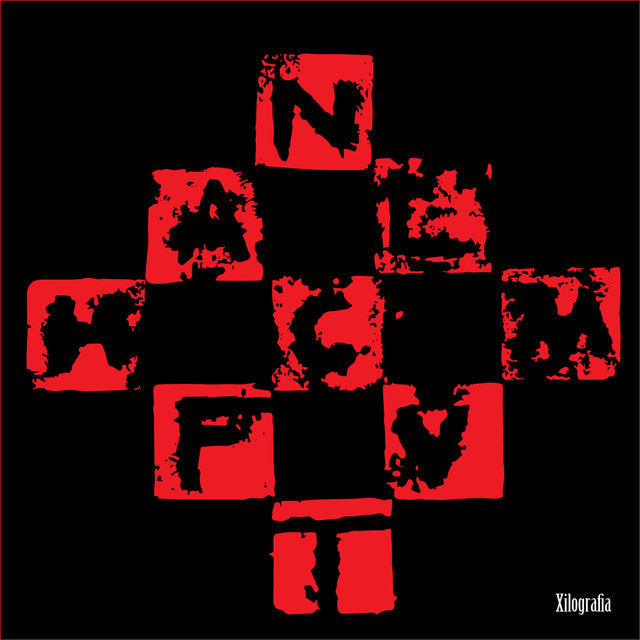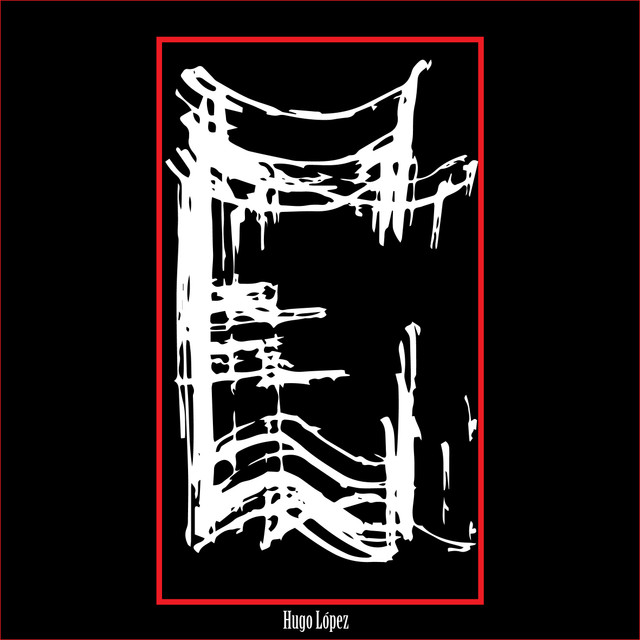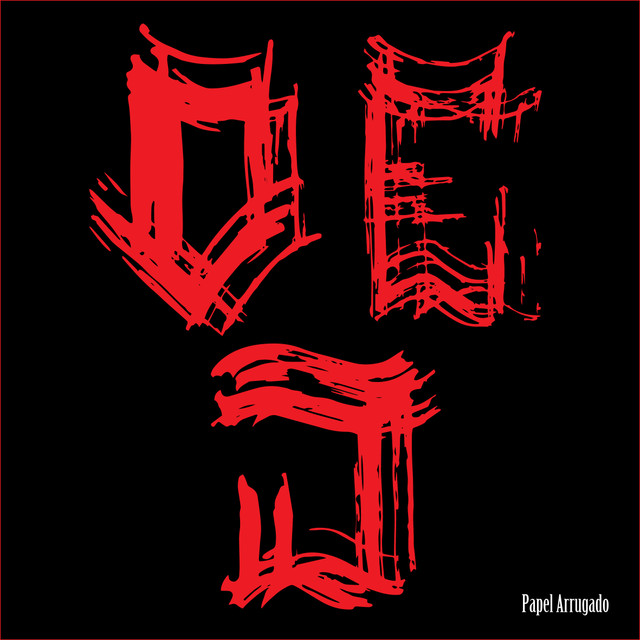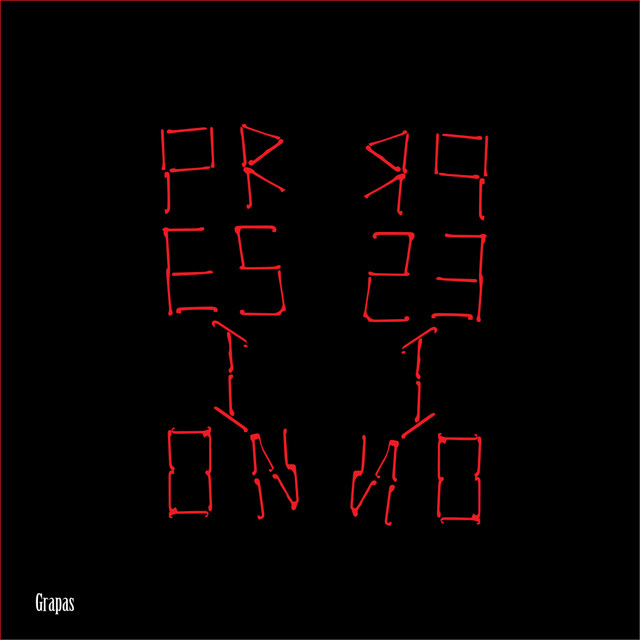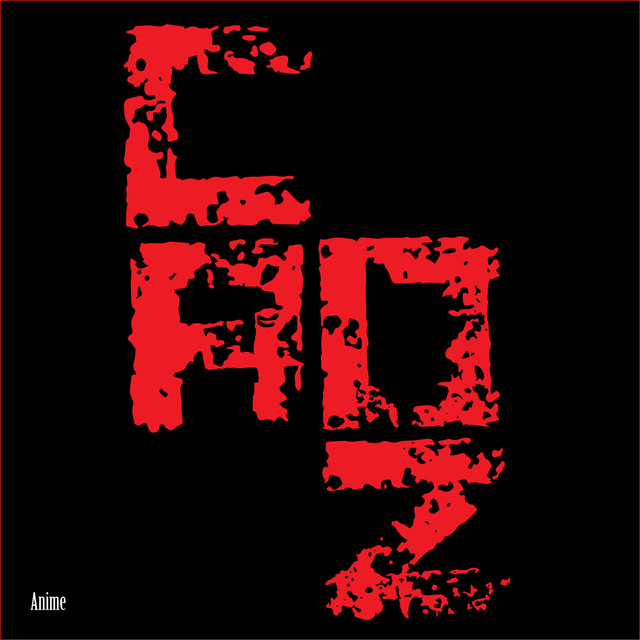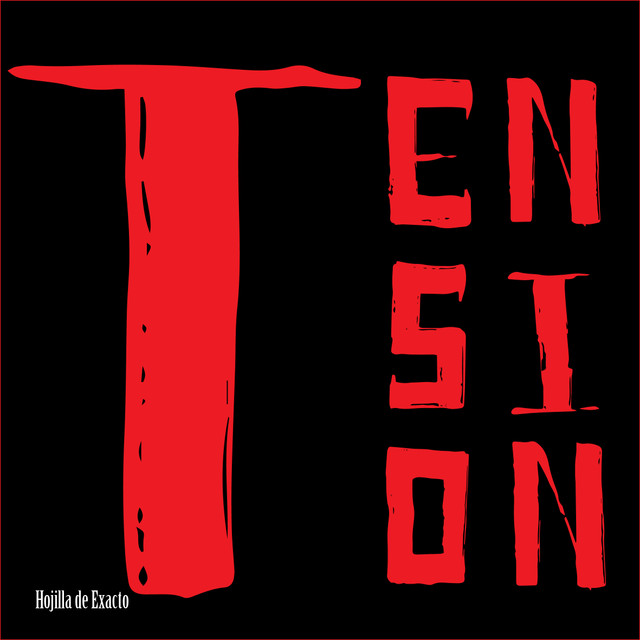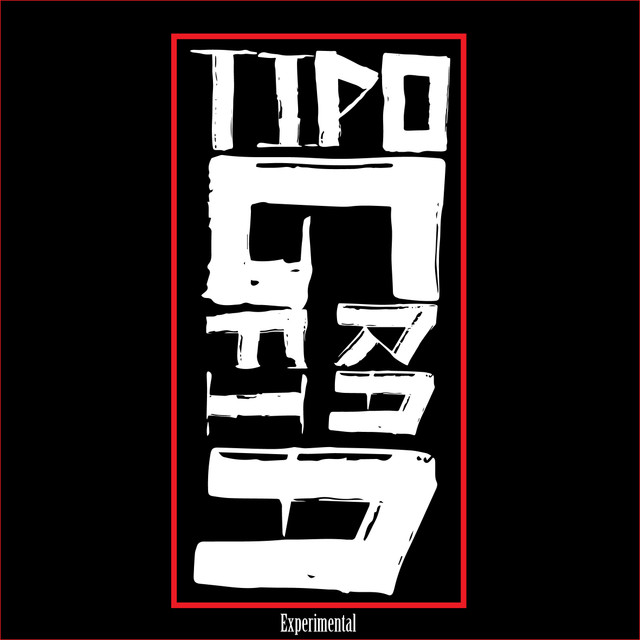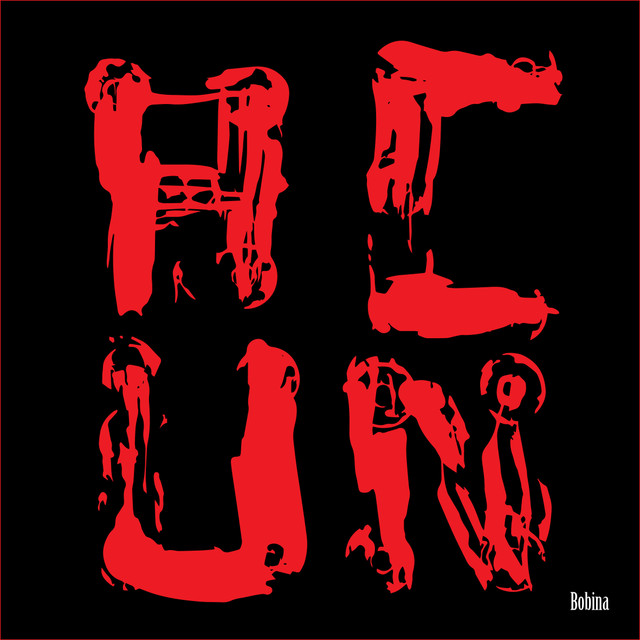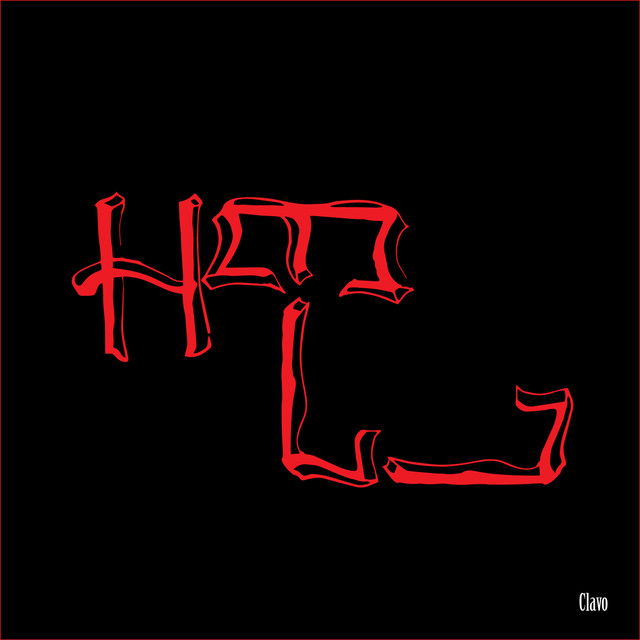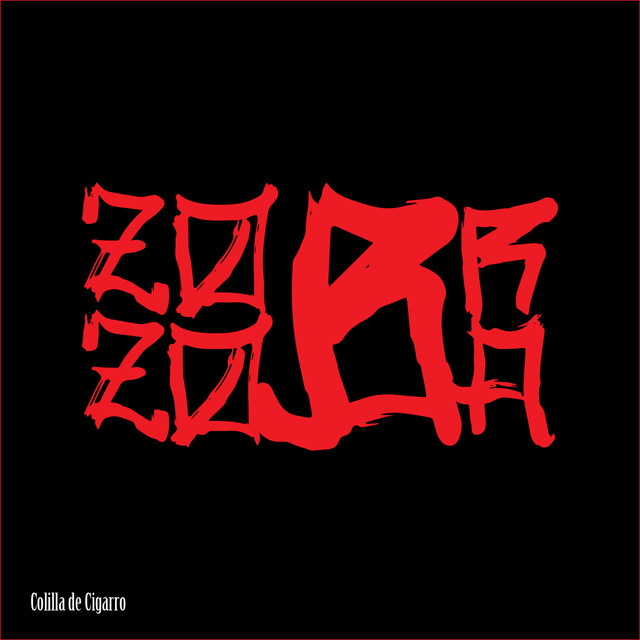
Catalogo de Tipografía Experimental : Tensión
El proyecto era construir un catalogo de tipografía experimental , utilizando materiales poco comunes para esta tarea, materiales y objetos que menciono en el catalogo.
Como concepto me base en la Tensión, sin más que decir, les presento el catalogo.